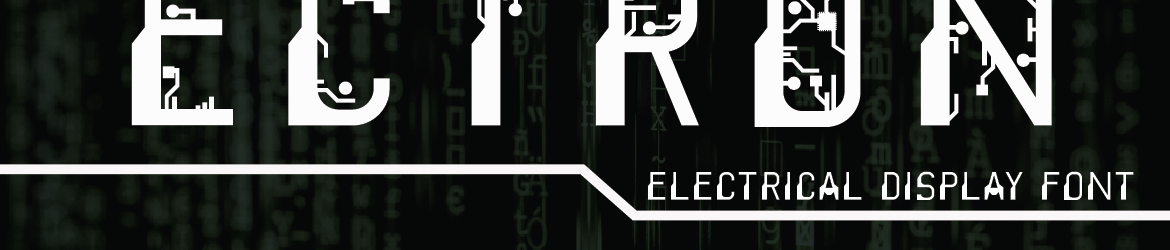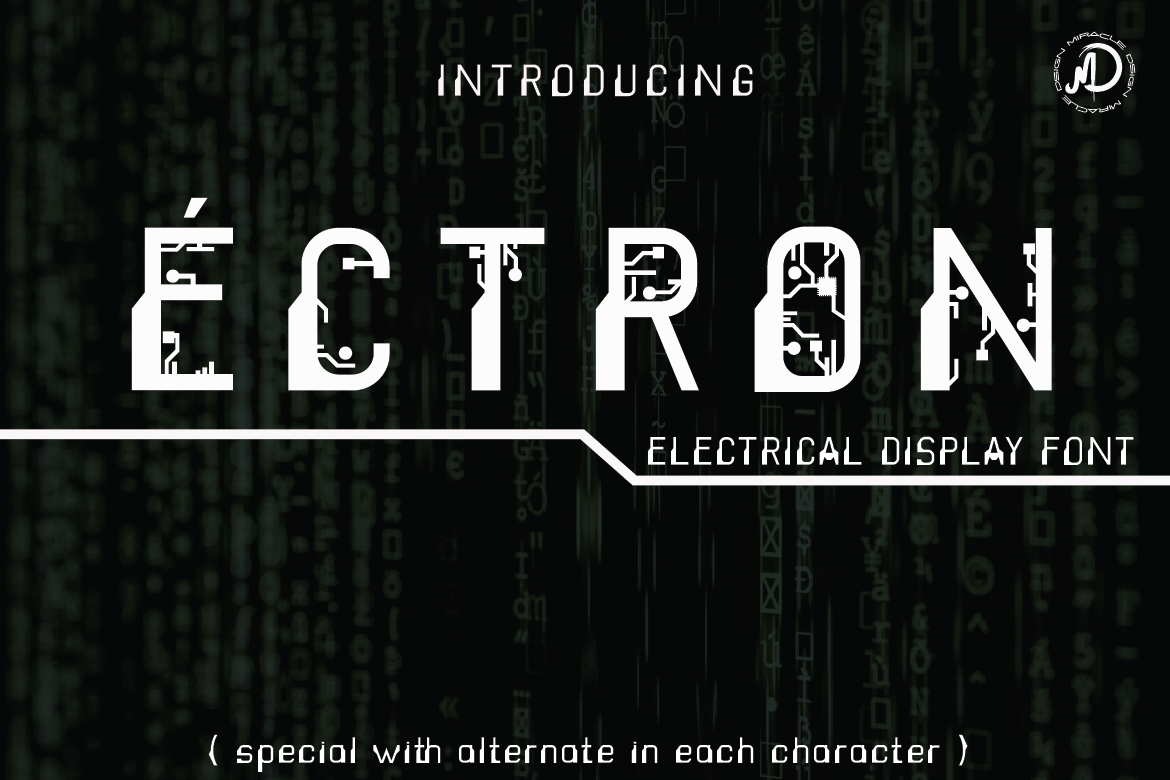
ECTRON Font – Fonte Grátis
ECTRON Font
A ECTRON Font é uma família de tipo gótico sem serif que apresenta características san-serif únicas, elegantes e encantadoras. Suas qualidades tornam-na perfeitamente adaptável a diversos projetos de design tanto para uso formal quanto informal. Esta fonte é realmente incrível, oferecendo flexibilidade para qualquer aplicação em designs variados. Além disso, a ECTRON vem equipada com alternativas para cada caractere, um recurso que facilita o seu uso para criar títulos e textos de alta qualidade. Este conjunto de caracteres versátil não só simplifica a criação de design visual, mas também adiciona uma diversidade única ao seu trabalho. Ao explorar esta família de tipo gótico sem serif, você terá à disposição um recurso que é tanto criativo quanto funcional, perfeito para qualquer projeto de design. ECTRON não apenas oferece opções variadas e interessantes em termos de estilo, mas também ajuda a criar textos e títulos impressionantes.